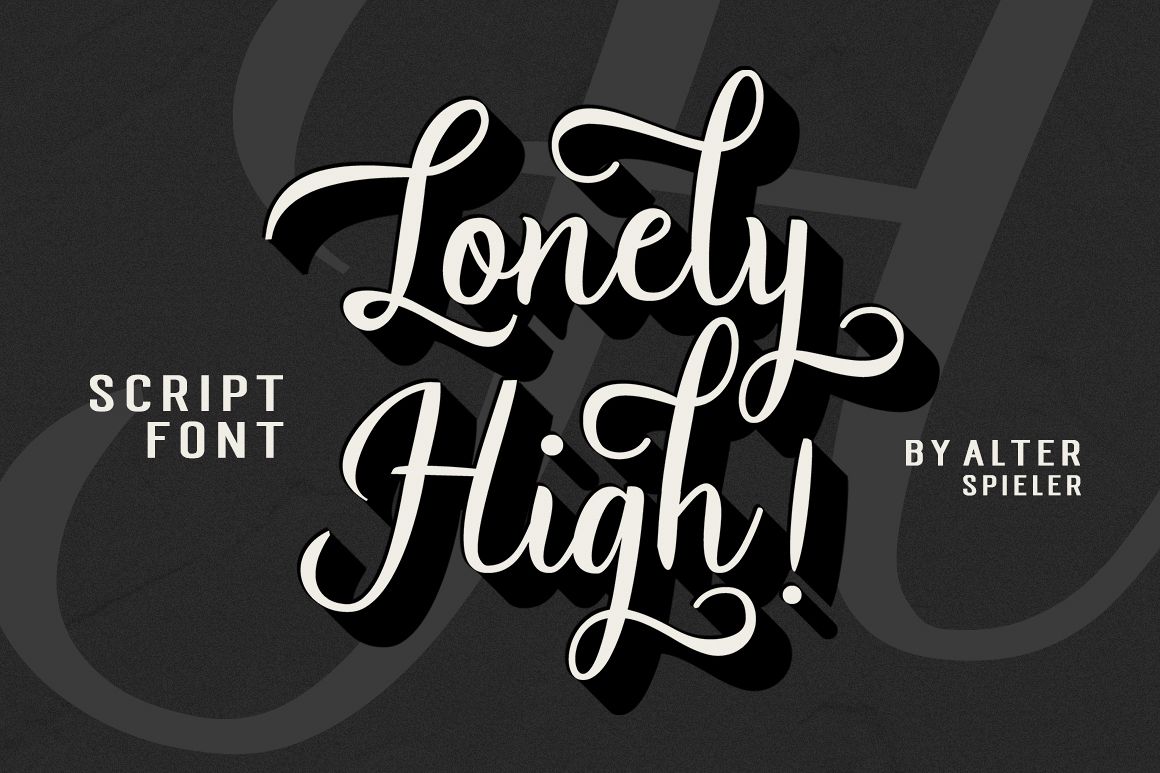
Lonely High
Lonely High adalah kaligrafi modern yang indah dan unik,
Font ini memiliki karakter gaya yang sederhana dan menarik untuk berbagai kebutuhan desain saat ini, Anda dapat menggunakannya untuk bordir, sablon, kartu nama, cutting, branding, dll.
Lonely High memiliki semua huruf besar dan kecil, juga memiliki alternatif, multi bahasa, pengikat, angka, tanda baca.